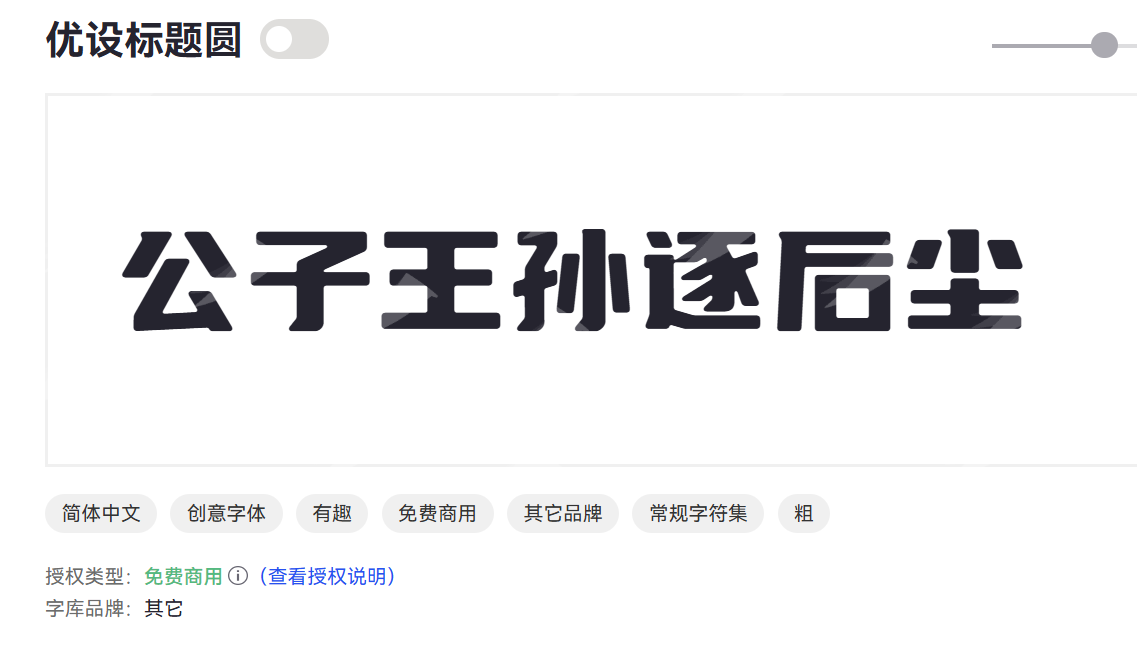
广告字体大全,10 款适合广告场景的字体分享
什么是广告字体,广告字体就是专门用于广告宣传、品牌推广中的文字设计。当我们谈论广告字体时,不仅仅是把信息写出来那么简单,它的选择直接关系到广告的整体视觉效果、信息的传达效率,甚至能影响消费者对品牌的初印象和情感认知。本文介绍10 款适合广告场景的字体,帮助大家做好广告设计。
一、5款可以免费商用的广告字体
站酷文艺体
站酷文艺体是由站酷网联合多位设计师共同开发的一款免费商用中文字体。它以其独特的文艺气质和手写感设计,迅速在设计圈中流行开来,成为众多设计师在设计广告素材的选择。
站酷文艺体笔画结构带有明显的书写感,融入了手写体的自然与灵动,赋予文字一种轻松、随性的文艺气息。所以非常适合品牌标志、产品包装、宣传海报、书籍封面、UI设计、短视频字幕、社交媒体配图等需要营造文艺、清新、亲和力氛围的场景。
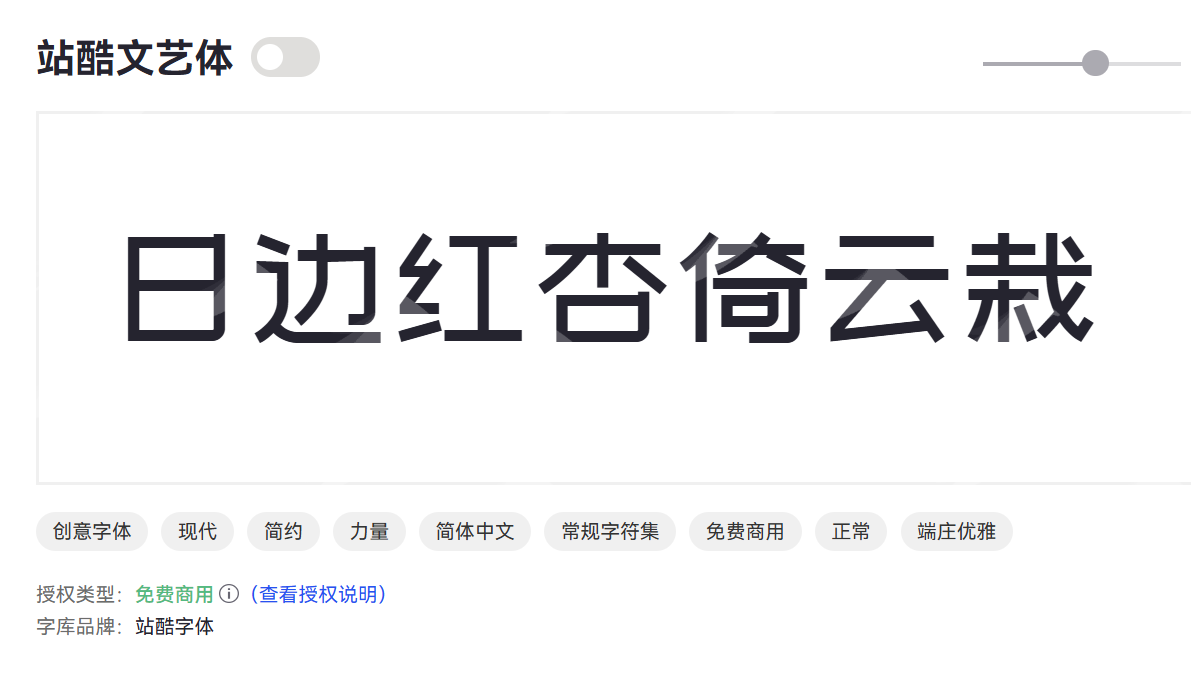
优设标题圆
优设标题圆是由优设网推出的一款专为标题设计打造的免费商用字体。独特的圆角处理和现代感,旨在为各种设计项目提供强大的视觉吸引力。
优设标题圆笔画粗细对比适中,字形结构稳定,在作为标题使用时能够迅速抓住观者的注意力。尤其适合电商广告、品牌宣传、活动海报、游戏界面等需要突出标题、强调重点的场景。
郑庆科黄油体
郑庆科黄油体是一款极具个性和趣味的手写风格字体。其名字“黄油体”形象地描绘了字体圆润、柔软、富有流动感的特点,我经常使用黄油体作为广告设计的字体。
也字工厂柳叶体
也字工厂柳叶体是一款充满东方古典韵味和书法艺术美感的字体。也字工厂柳叶体整体风格典雅、含蓄,散发出浓郁的东方古典气息,适合营造诗意和艺术氛围。适用于文化艺术品、茶饮、古风服装、国潮品牌等场景。
仓耳舒圆体
仓耳舒圆体是一款由仓耳字库开发的现代风格圆体字体。所有的笔画末端和转角都经过柔和的圆角处理,使得字体整体视觉感受非常舒适、温和。
仓耳舒圆体适合用于企业官网、APP界面、产品说明书、宣传册、等需要营销宣传等广告场景。
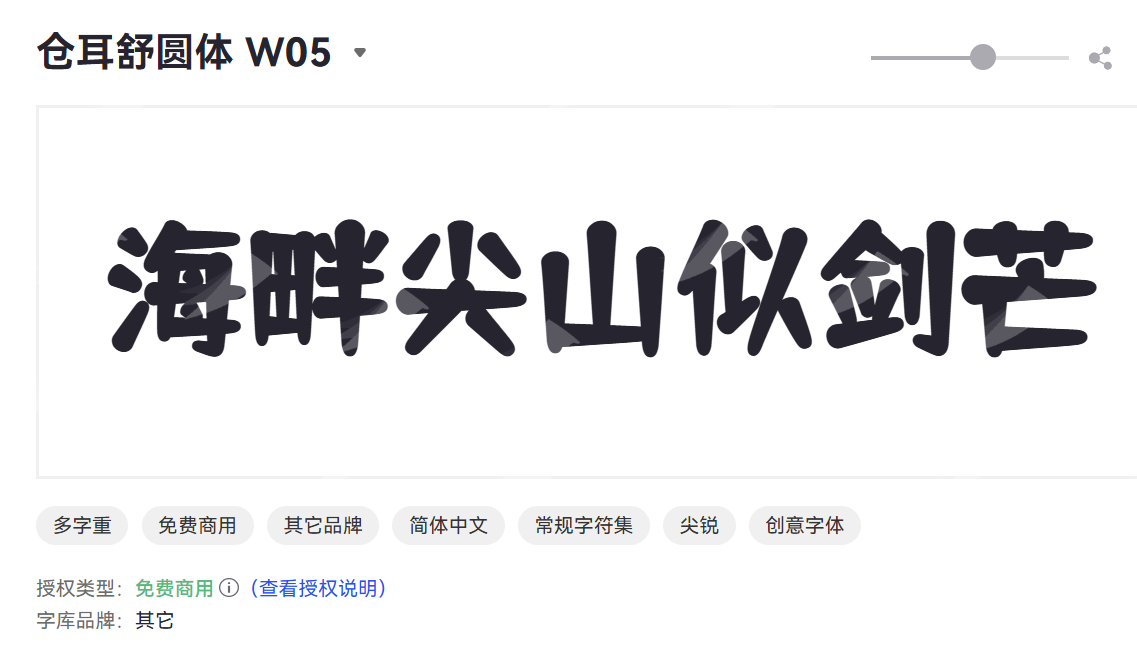
二、5款可以授权商用的广告字体
汉仪花仙子
汉仪花仙子是汉仪字库推出的一款充满浪漫、梦幻色彩的艺术字体。它以花朵和仙子的形象为灵感,笔画纤细流畅,带有独特的装饰性,专为展现柔美、优雅和少女情怀而设计。
汉仪花仙子能够迅速吸引女性和年轻群体的目光,提升品牌的吸引力和记忆点。提升广告的效率。
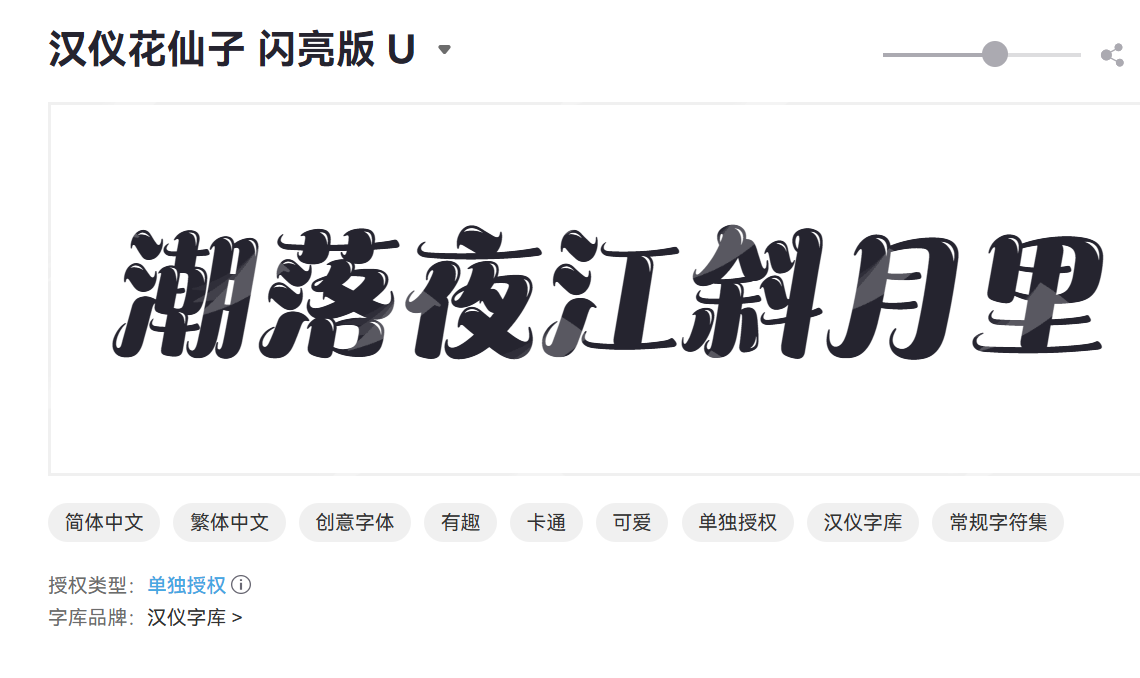
郑庆科帅黑体
郑庆科帅黑体是一款现代感十足的无衬线黑体字体。虽然需要授权商用,但很多设计师都会在设计营销物料的时候,使用这款广告字体。郑庆科帅黑体适用于科技、汽车、运动等男性用户群体。
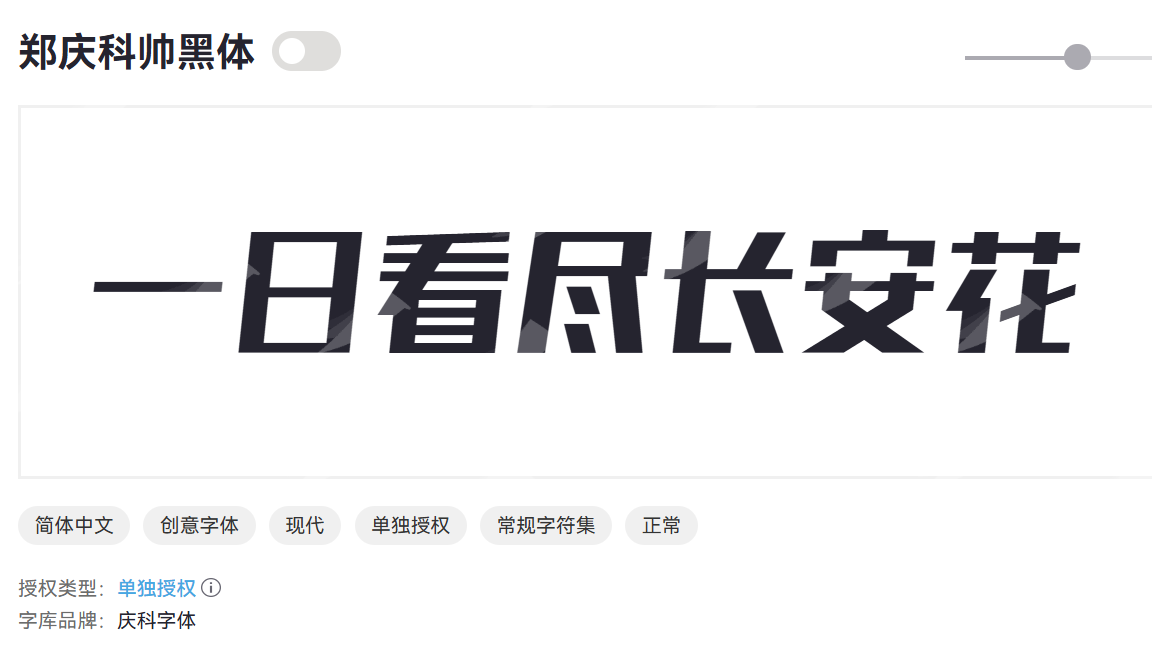
Aa原味吐司
Aa原味吐司是一款充满质朴、自然气息的手写风格字体。字体笔画介于手写与印刷体之间,带有不完美的随机感,但整体协调,充满手工制作的温度和朴实感。非常适合咖啡馆、烘焙店、手工制品、文创商品等场景,使用在标题的广告字体。
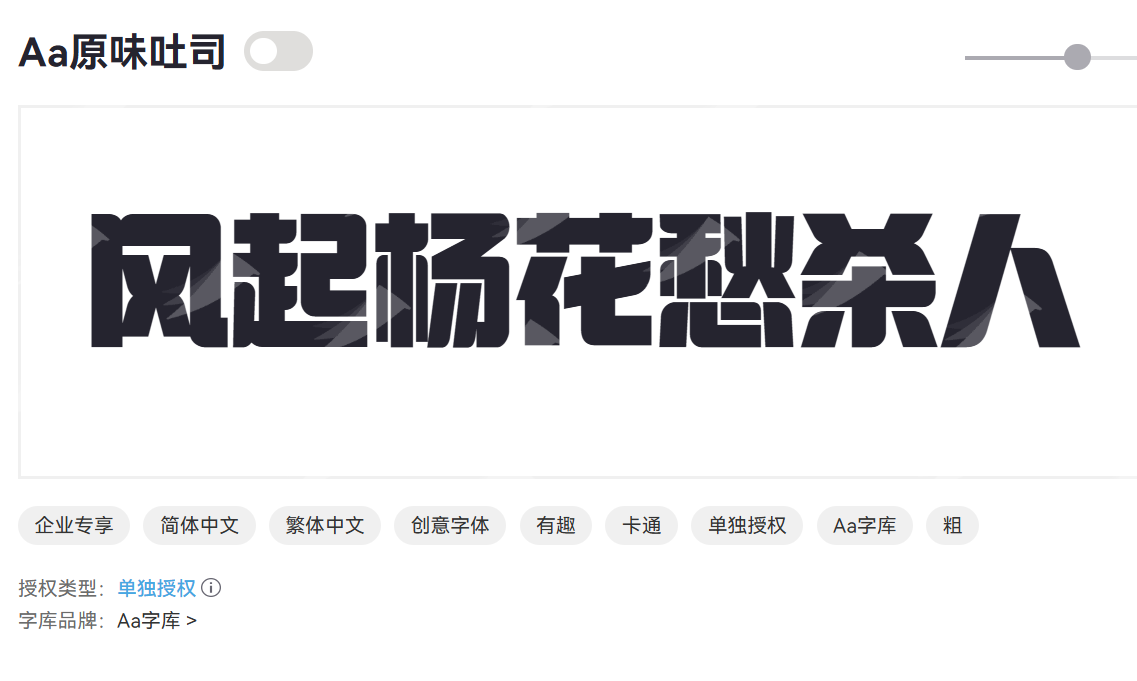
汉仪超级战甲
汉仪超级战甲是汉仪字库推出的一款极具未来感、科技感和力量感的创意字体。
汉仪超级战甲字体结构粗壮厚重,重心稳定,传递出一种坚不可摧、蓄势待发的力量感。适用于游戏、电影、科幻小说、科技产品、军事装备、重工业、汽车、运动鞋服等需要展现未来、科技、力量、速度、硬核、酷炫的场景。
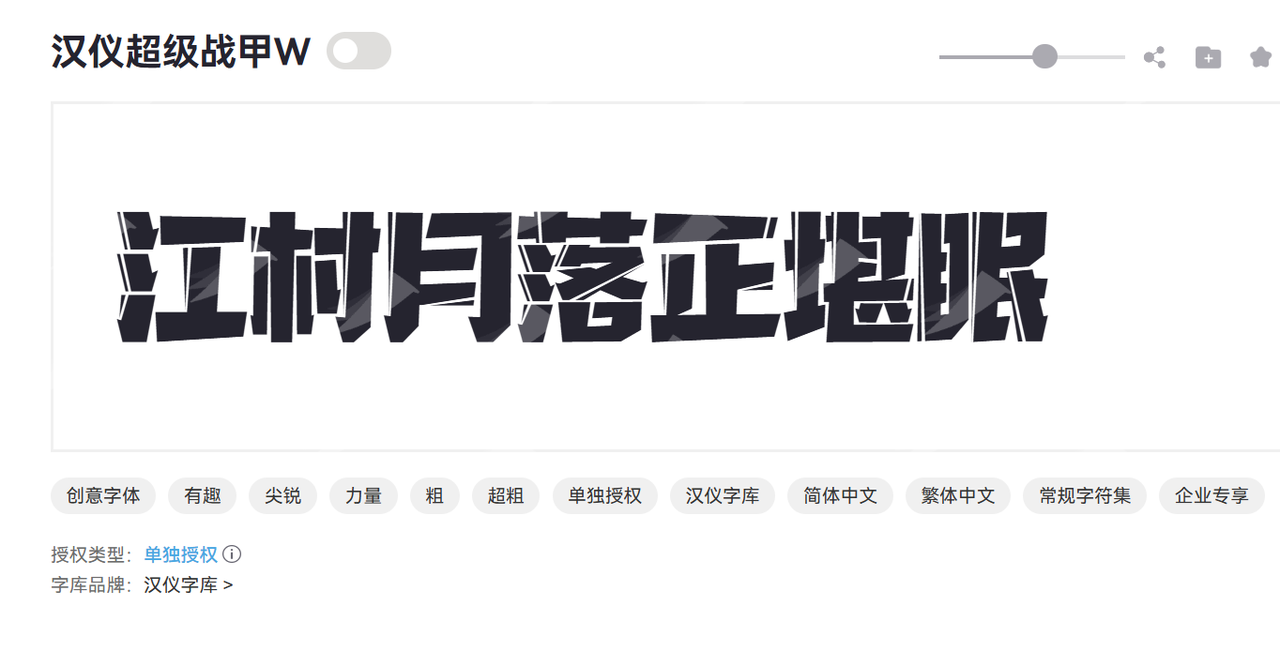
Aa轩辕体
Aa轩辕体是一款充满东方古韵和磅礴气势的字体,整体字形开阔舒展,雄浑有力,给人一种宏大、庄严、肃穆的感觉。
非常适合国潮品牌、历史题材影视、博物馆展览、文化旅游、传统工艺品、等需要传达厚重历史感、民族自豪感、庄重权威感的场景。
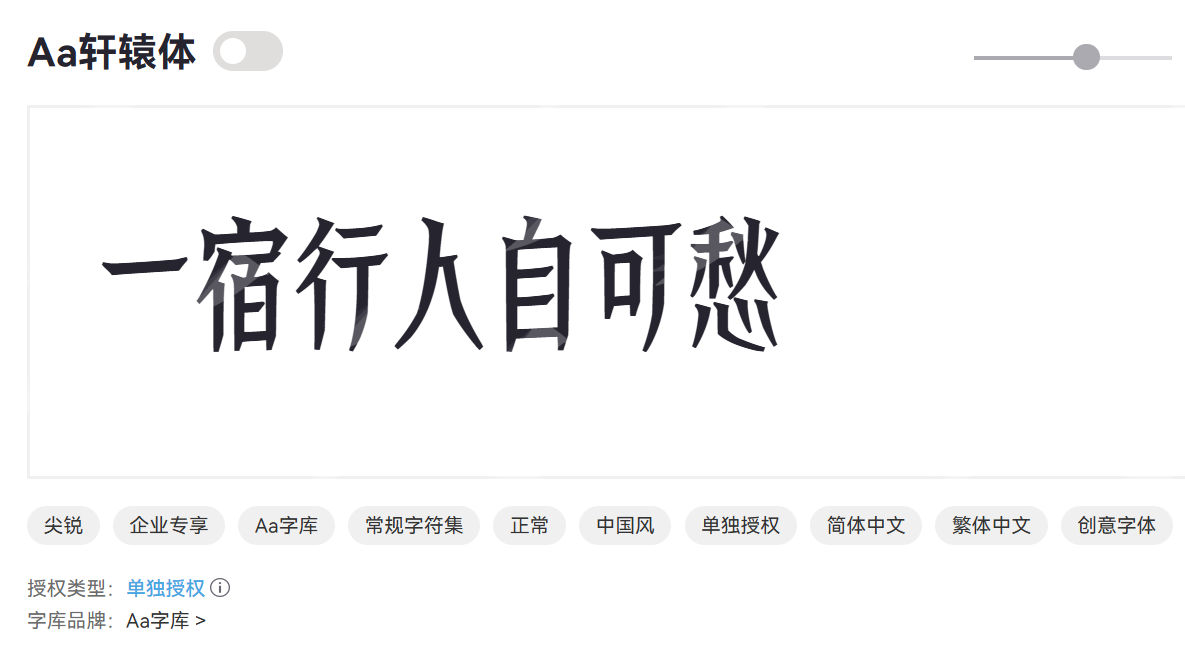
三、广告字体的作用
- 吸引眼球快速抓取注意力:
在信息爆炸的时代,广告需要在一瞬间抓住受众的目光。在广告投放中尤其重要,广告字体选择的好,可以提升整体的广告 ROI。
- 提升信息可读性与辨识度:
无论字体多么美观,如果信息难以阅读,那它就失去了广告的意义。优秀的广告字体在追求美感的同时,更要确保文字清晰易辨,让受众在短时间内理解广告内容。
- 增强品牌记忆点:
很多知名品牌的Logo或广告语都离不开其独特的字体设计。这种视觉上的统一性,有助于消费者形成对品牌的稳定认知,加深记忆。